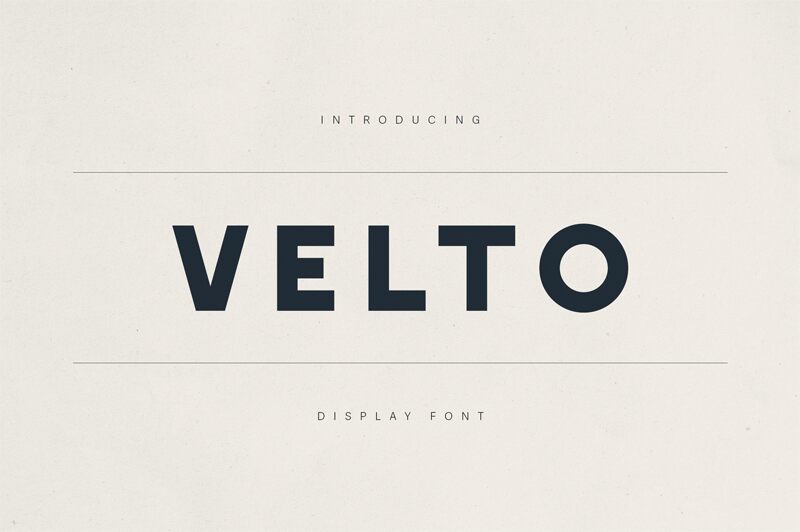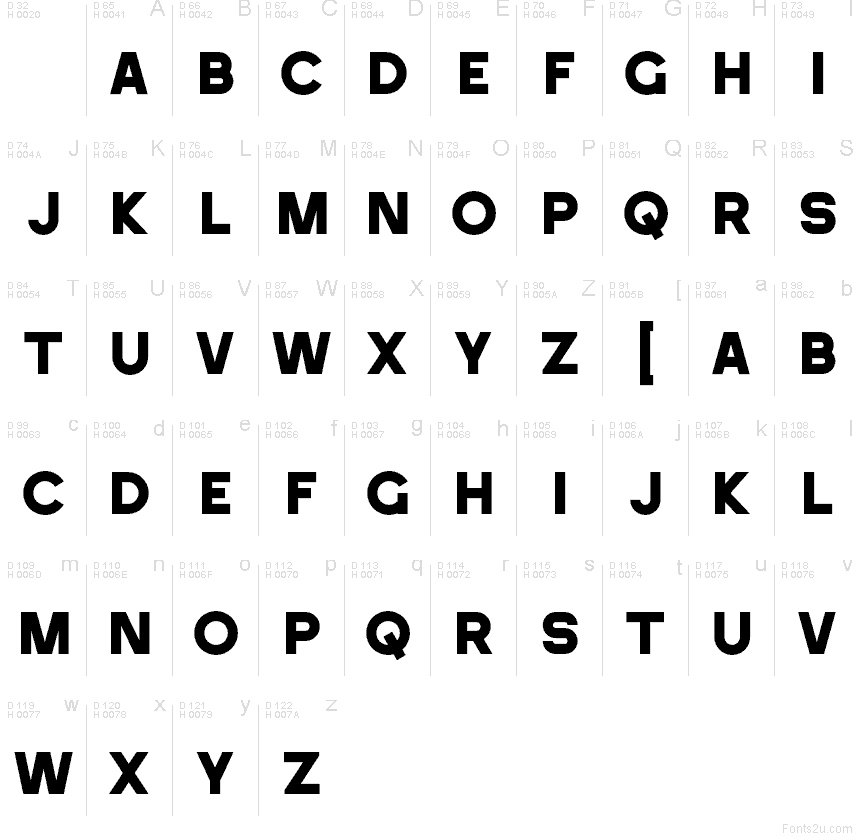
Velto ist eine kostenlose geometrische serifenlose Schrift, die durch stumpfe vertikale Schnitte und breite, kreisförmige Formen besticht, die dem Schriftbild eine kompakte, plakative Silhouette verleihen. Das Design wirkt durch seinen engen, direkten Rhythmus und die Kombination aus quadratischen Innenräumen mit einer fast monolinearen Strichstärke eher konstruiert als neutral.
Diese feste Form ist ideal für Poster, Branding, Überschriften, Verpackungen und Albumcover, bei denen kurze Wörter als massiver, schwarzer Block auf der Seite wirken sollen. Velto eignet sich zudem hervorragend als Anker für Logos und Interface-Titel, besonders wenn Sie nach schlichten Formen suchen, die dennoch genügend visuelle Präsenz besitzen, um durchdacht und einprägsam zu wirken.